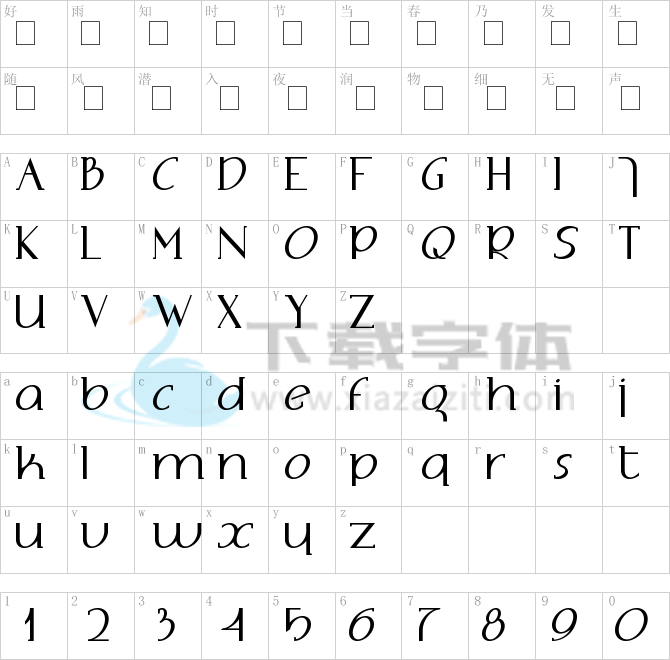
Adolphus Serif.ttf字体下载,这款字体结构工整、笔画清晰,兼顾美观与易读性,适用于标题、正文、海报、包装、LOGO 等多种场景。字形优雅稳定,风格百搭耐看,适配日常排版与创意设计,让文字呈现更舒适、更具质感。Adolphus Serif.ttf字体下载一笔一画,皆是细节,以均衡的比例、流畅的线条打造舒适视觉体验,字形端正大气,风格简约现代。无论是商业设计、品牌宣传还是日常排版,都能轻松驾驭,让文字更有格调与力量。Adolphus Serif.ttf字体下载字体下载。
Adolphus Serif.ttf图片展示
• 字体名称:Adolphus Serif
• 字体全名:Adolphus Serif